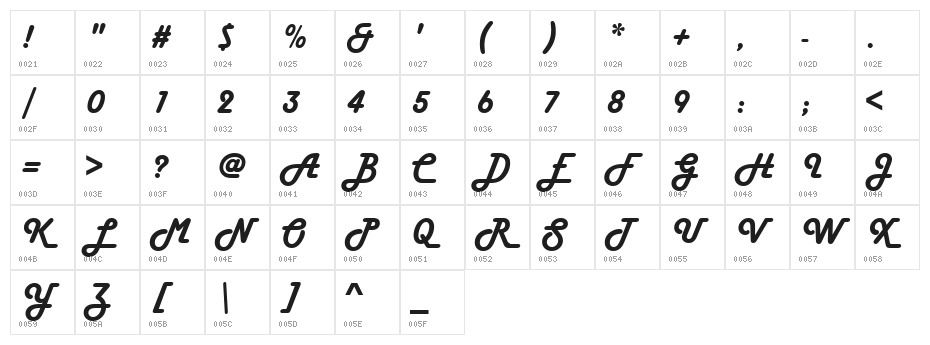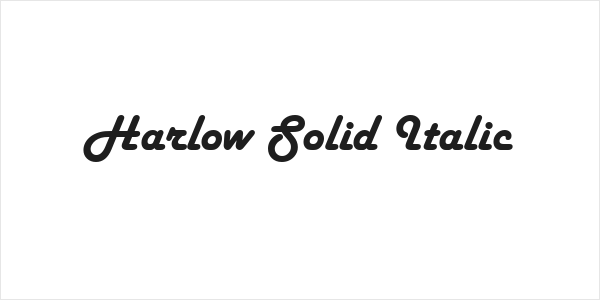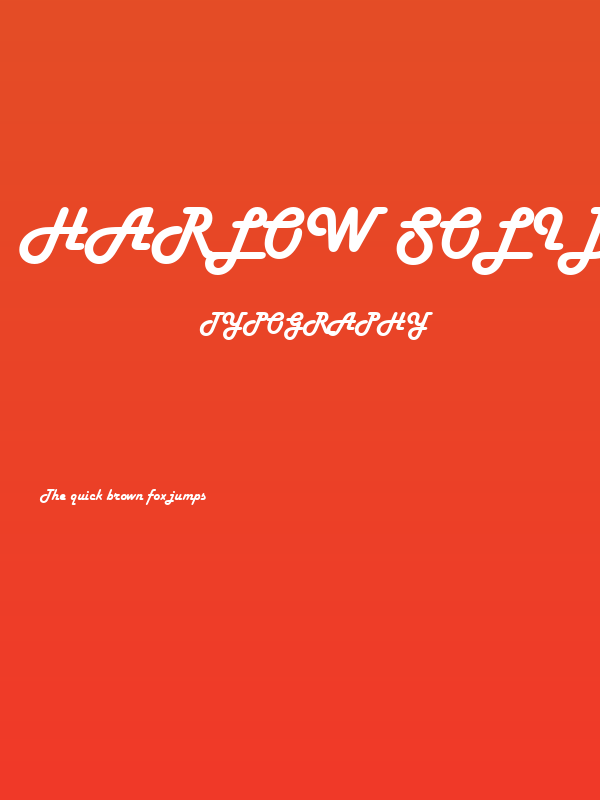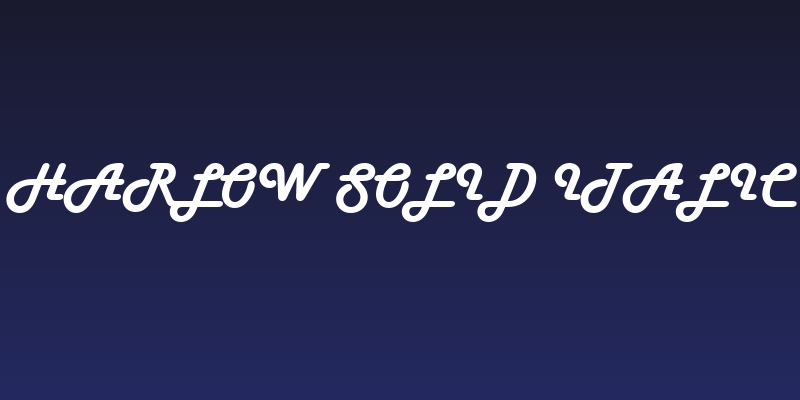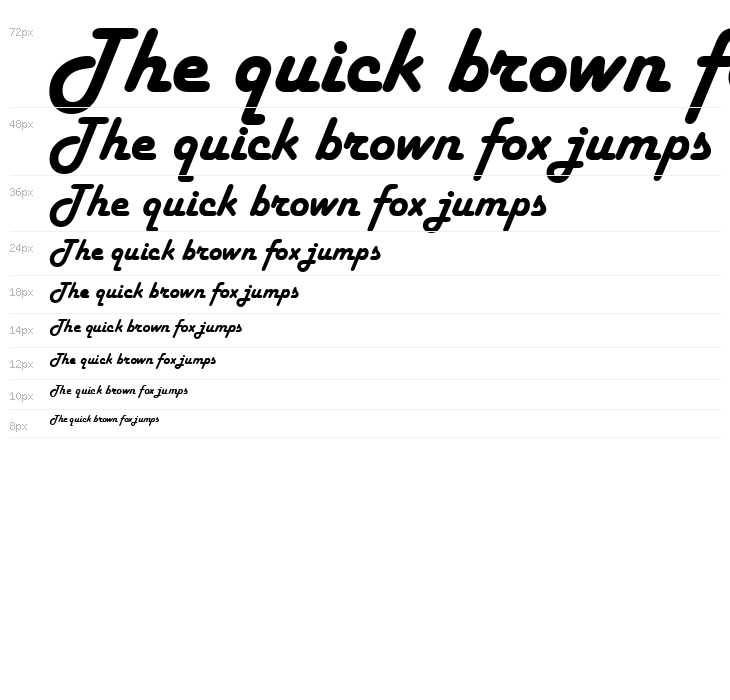
Harlow Solid Italic Font
✎ Script
| Anwendungsfall | Logos, Invitations, Greeting Cards |
| Vorgeschlagene Projekte | Ideal for invitations, greeting cards, logos, and branding materials that require a touch of elegance and flair. |